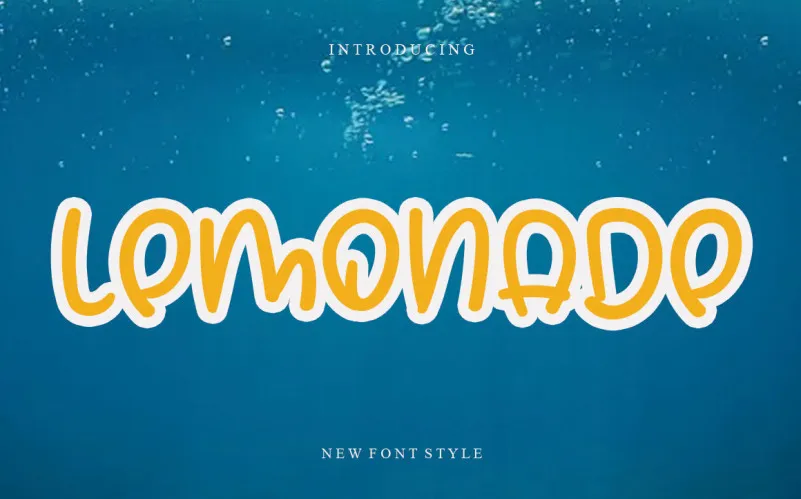
Lemonade Font é uma fonte escrita a mão única, divertida e amigável que combina os elementos do handwritten com as qualidades sofisticadas dos tipos de letra para decorar. Perfeita tanto para Instagram como para a criação de projectos DIY, esta fonte transformará qualquer ideia criativa em um verdadeiro trabalho de arte. Ideal tanto para quem busca uma paleta colorida e vibrante, quanto para aqueles que desejam algo mais relaxado e leve na personalização do seu projeto. Lemonade Font é o tipo de font perfeito para tornar seus projetos ainda mais especiais.